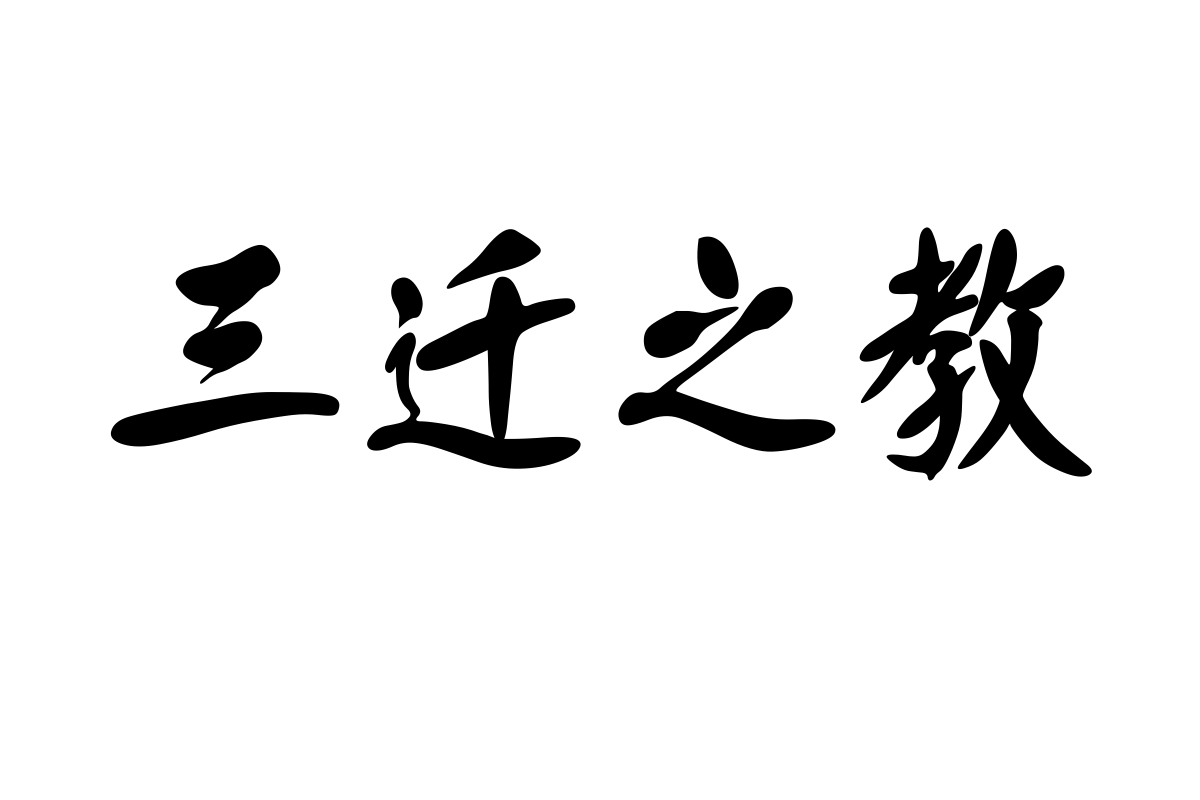
汉标粗犷体是一套具有强烈视觉冲击力和艺术风格的字体。它由汉标公司设计,结合了现代审美和传统书法元素,创造出一种独特的字体风格。
汉标粗犷体的特点包括:
1. 字形结构:汉标粗犷体的字形结构独特,笔画粗细不一,线条流畅而有力,给人一种强烈的视觉冲击感。
2. 风格特点:汉标粗犷体具有强烈的个性和艺术性,适合用于广告、海报、包装等需要突出表现力的设计领域。同时,它也适用于需要传达力量、激情和活力的场合。
3. 适用范围:汉标粗犷体适用于各类商业设计、艺术创作、广告传媒等领域,能够为作品增添一份独特的魅力和个性。
总之,汉标粗犷体是一种极具个性和艺术性的字体,适合用于需要突出表现力的设计领域,为作品增添一份独特的魅力和个性。